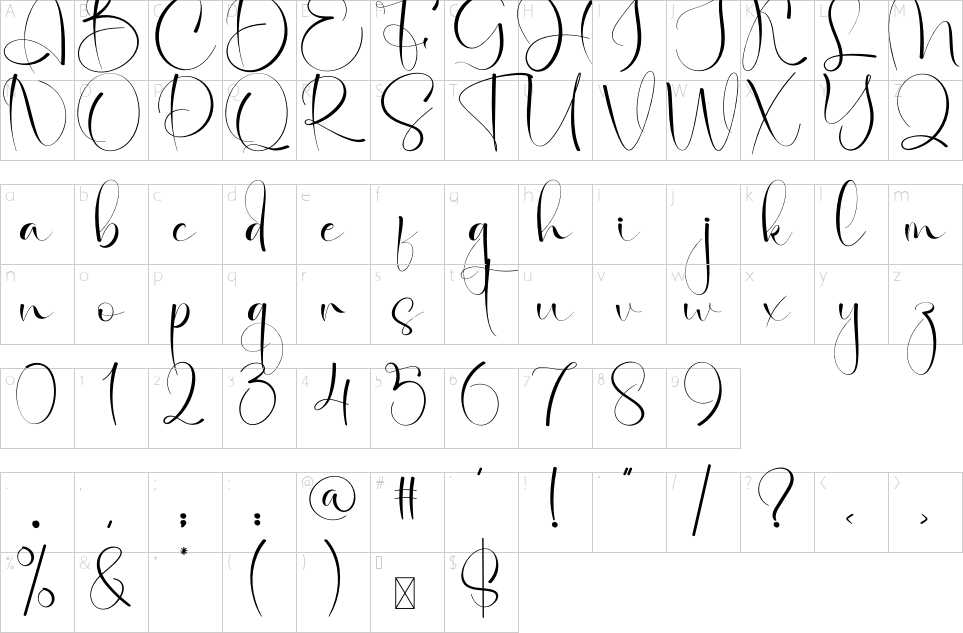
Descubra o encanto da Amsterdam Font, uma elegante e sofisticada fonte para Windows e Mac que está disponível gratuitamente. Desenhada por scratchones, a Amsterdam Font enriquece qualquer layout com sua perfeita combinação de linhas finas e espessas, proporcionando um visual profissional e sofisticado. Seu design único foi criado para atender aos criadores de conteúdo e profissionais de design que desejam adicionar um toque único a suas criações digitais. Com uma facilidade de uso óbvia, a Amsterdam Font torna-se a escolha perfeita para quem busca uma fonte de qualidade sem precisar gastar dinheiro. Através de downloads simples, a fonte já foi instalada por 709 usuários, demonstrando seu valor e popularidade. Descubra por si mesmo o poder da Amsterdam Font e traga um toque especial a seu design.